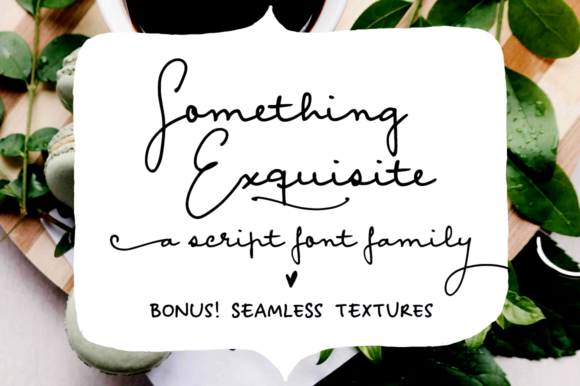
Something Exquisite
Ulasan Lengkap tentang Font “Something Exquisite” – Elegansi dalam Setiap Goresan
Jika Anda sedang mencari font yang memadukan keunikan, keanggunan, dan sentuhan personal, Something Exquisite adalah pilihan yang tak boleh dilewatkan. Dirancang sebagai font tulisan tangan yang eksklusif, ia memberikan nuansa mewah sekaligus hangat pada berbagai proyek desain. Baik untuk undangan pernikahan, kartu ucapan, logo, maupun materi branding, font ini berhasil menonjolkan karakteristik personal yang sulit dicapai oleh font standar.
Keunggulan Utama Something Exquisite
- Desain Handwritten yang Otentik – Setiap huruf tampak seperti ditulis dengan pena kaligrafi, memberikan kesan personal dan elegan.
- Versatilitas Tinggi – Cocok untuk wedding invitations, thank you cards, kartu ucapan, logo, serta desain grafis lain yang memerlukan sentuhan mewah.
- Keterbacaan yang Baik – Meskipun bergaya skrip, bentuk huruf tetap jelas dan mudah dibaca pada ukuran kecil maupun besar.
- Paket Lengkap – Menyertakan variasi berat (regular, bold) serta karakter khusus untuk bahasa Portugis, sehingga Anda tak perlu khawatir tentang glyph yang hilang.
Pengalaman Penggunaan di Berbagai Media
Berikut beberapa contoh real‑world di mana Something Exquisite bersinar:
- Undangan Pernikahan – Kombinasi dengan warna pastel dan elemen floral membuat undangan tampak romantis dan eksklusif.
- Kartu Ucapan Terima Kasih – Sentuhan tulisan tangan menambah rasa personal, cocok untuk klien premium atau acara keluarga.
- Logo Brand Luxury – Menggunakan huruf kapital yang elegan, font ini memberikan identitas yang kuat dan berkesan mewah.
- Materi Promosi Digital – Pada banner dan posting media sosial, Something Exquisite menarik perhatian tanpa terasa berlebihan.
Kenapa Pilih Something Exquisite untuk Proyek Anda?